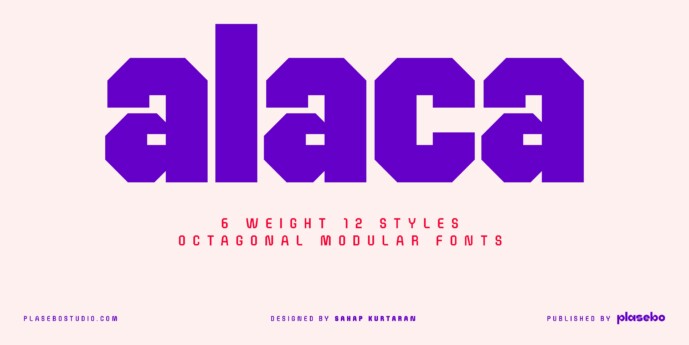
Alaca Complete Family Font
Designer: Plasebo Studio
À propos de la famille Alaca Police
Le caractère Alaca a été conçu, sur la base de sa forme octogonale, comme une famille contemporaine, dynamique et moderne police .
Lors de la conception de la police de caractères Alaca, chaque glyphe a été doté d’une forme qui le relie aux autres glyphs.
Ainsi, l’harmonie entre les lettres a été portée à un niveau avancé.
La famille Alaca police se compose de 6 graisses et d’italiques correspondant à ces graisses.
Il peut être utilisé typographiquement comme logo, titre et texte police jusqu’à certaines tailles.